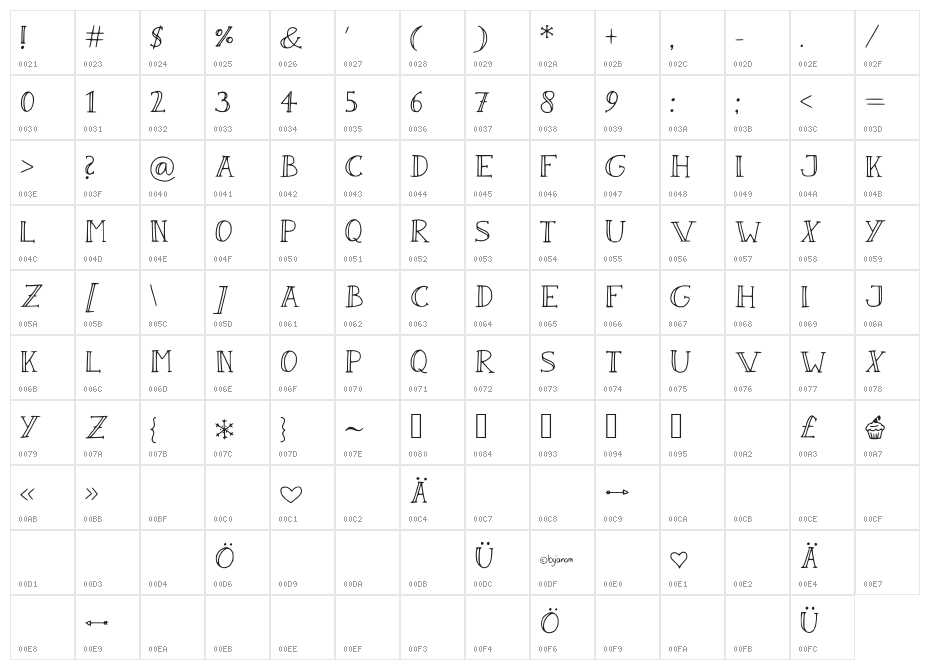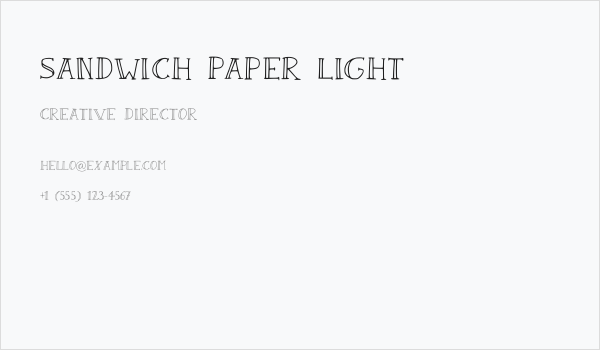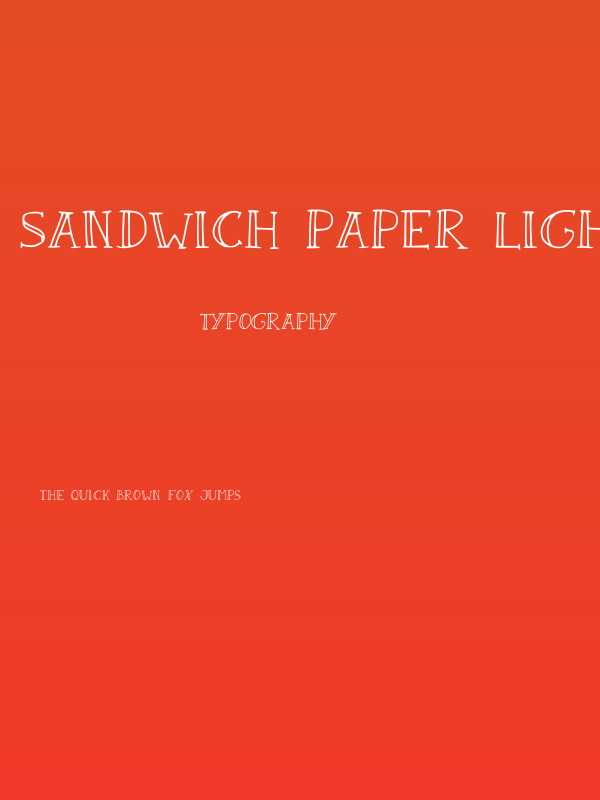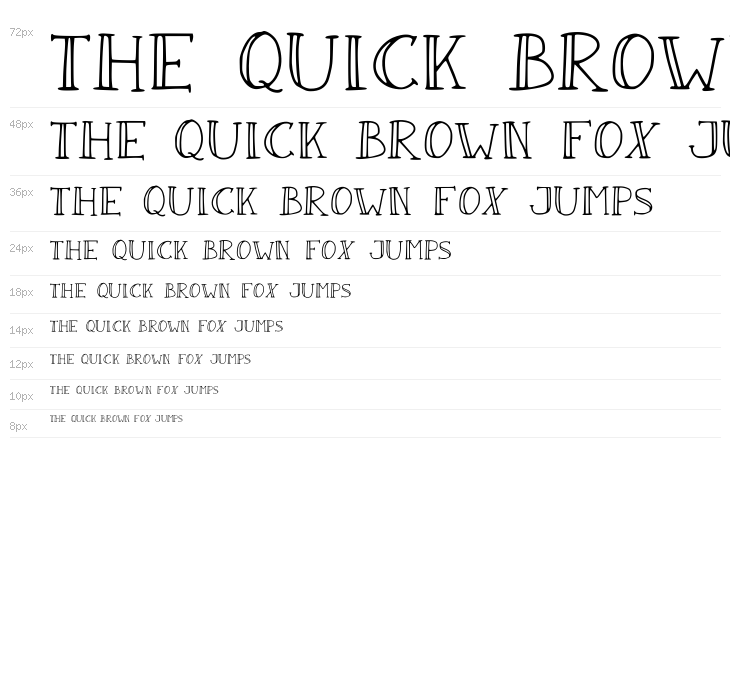
Sandwich Paper Light Font
✎ Modern
| Peso | Light |
| Categorie | Modern |
| Caso d'uso | Headlines, Logos, Invitations |
| Progetti proposti | Ideal for wedding invitations, luxury branding, editorial design, and elegant packaging. |